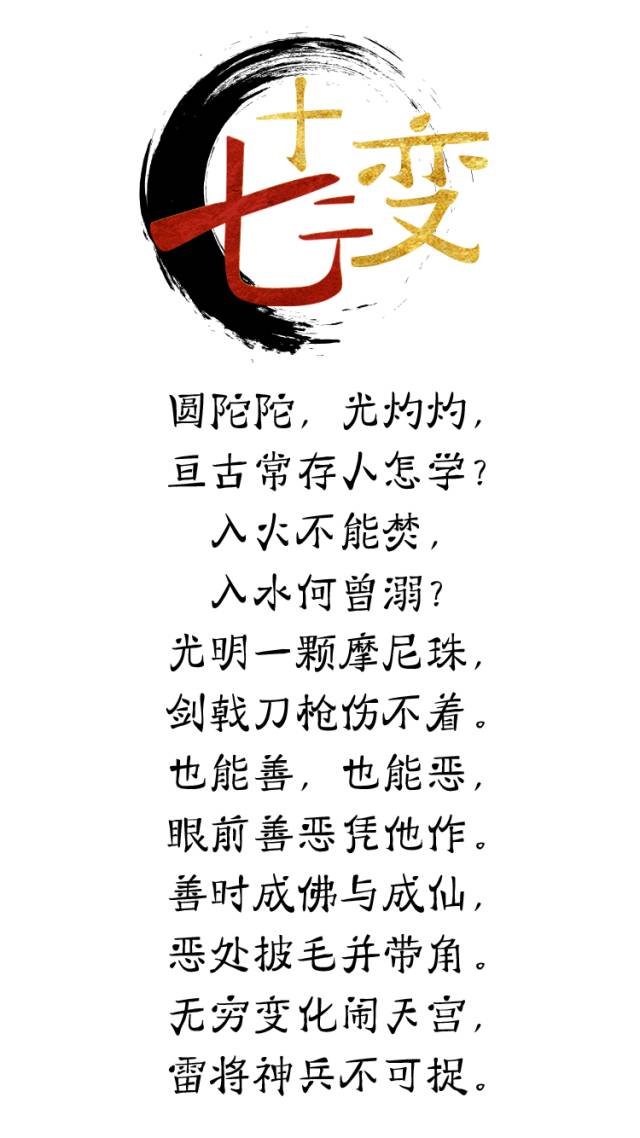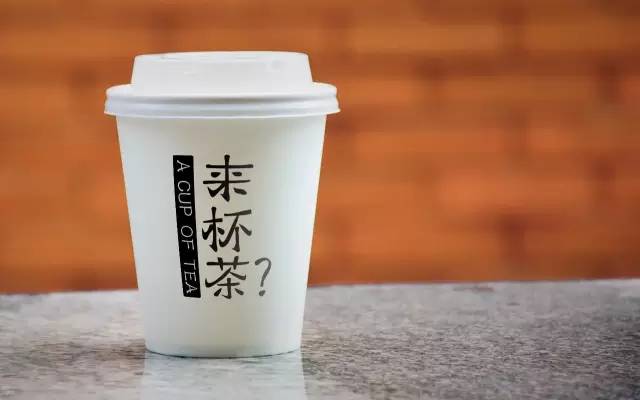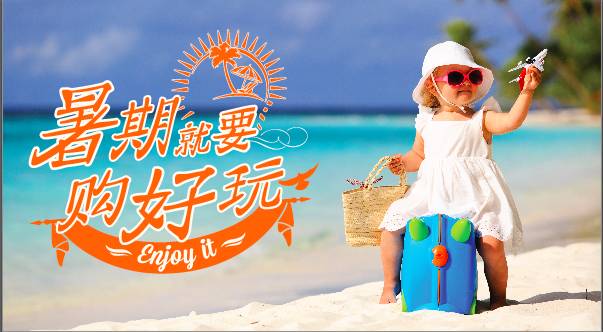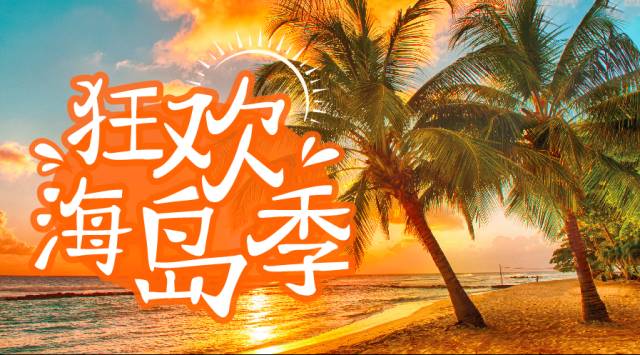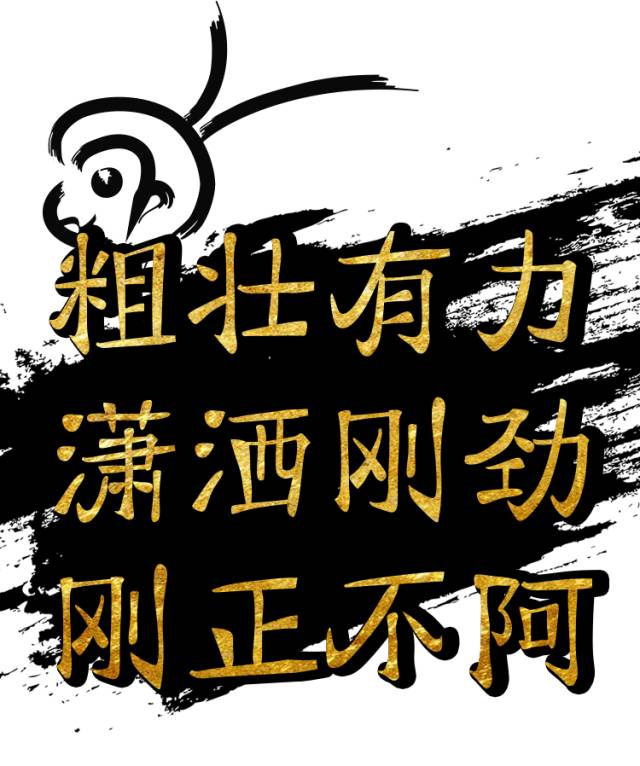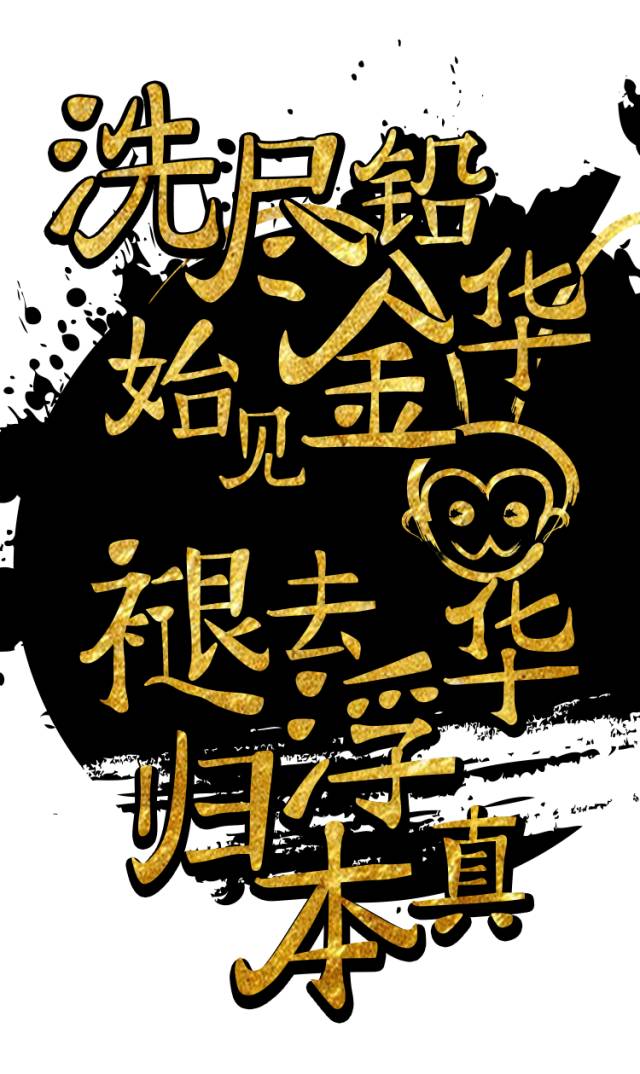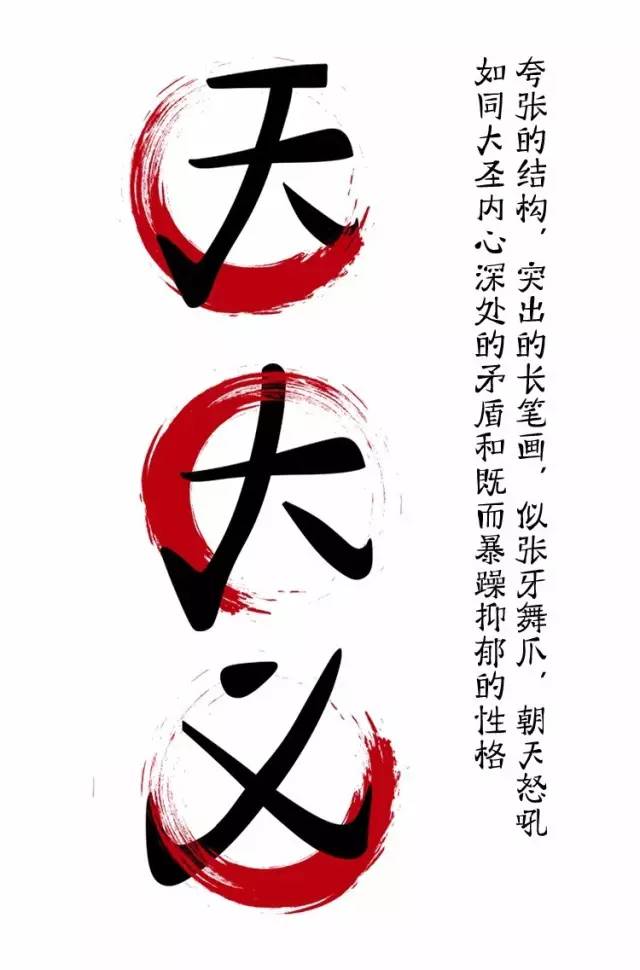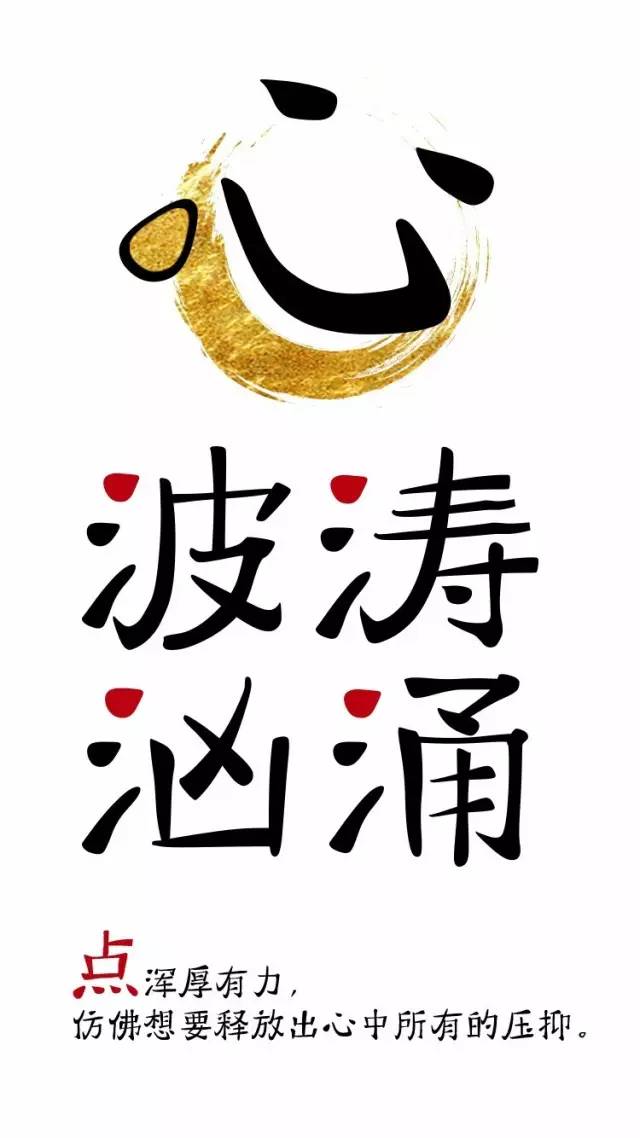
汉仪大圣体-汉仪大圣体字体介绍、案例、特点
大圣不畏险阻,西游记中在与唐僧师徒四人的冒险之旅中找回初心,完成自我救赎。这样的故事总会伴随着主人公矛盾的精神状态,而富有克己精神的字将笔画的张力合理的保持在恰如其分的结构内,令强张力与克制并存。
大圣体中一些简单的独体字,如“天”、“大”、“义”等。设计其夸张的结构,突出的一个长笔画,像是张牙舞爪,朝天怒吼的状态,试图描述出大圣内心深处的矛盾和既而暴躁抑郁的性格。“心”、“氵”中的第一点,浑厚有力,仿佛想要释放出心中所有的压抑。
“国”、“目”、“凶”等包围结构的字,褪去浮华,从容淡定,整体笔画的运用,模拟鹅软石的造型,历经时间岁月冲洗,更像是一种善心和童心去感化曾经那为所欲为的自我,看淡功名,回归初心。